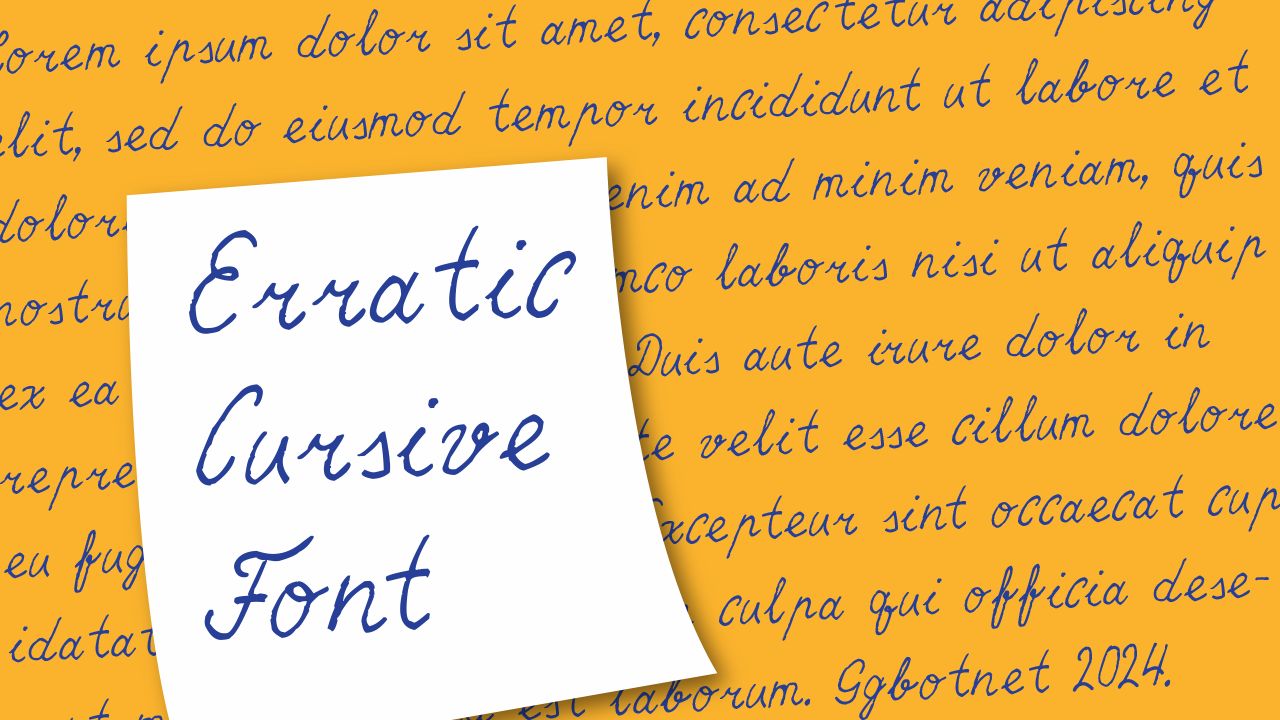
Шрифт «Erratic Cursive»
GGBotNet по лицензии Creative Commons Zero v1.0 Universal выложен бесплатный шрифт «Erratic Cursive» для того, чтобы все желающие могли его использовать в своих приложениях. Например, для визуализации записок или писем в приключенческой игре. Он имеет 2 начертания, 437 глифов и поддерживает 42 языка. Для лучшей визуальной эстетики настоятельно рекомендуется использовать курсив.